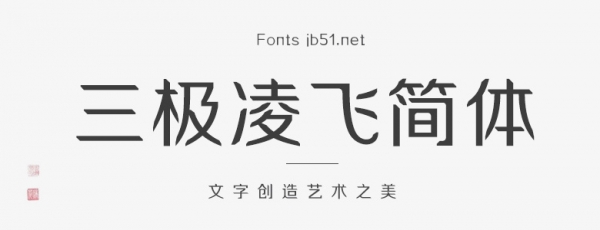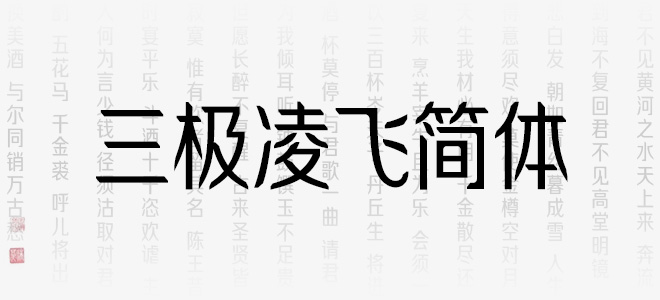
三極凌飛簡(jiǎn)體創(chuàng)意來(lái)自于鉛筆尖頭的外形,字形清新,結(jié)構(gòu)嚴(yán)謹(jǐn),起筆收筆都為斜角截?cái)啵卣髅黠@,整齊中賦予變化,易讀性強(qiáng)。適用于雜志、書(shū)刊、品牌廣告、文化用品包裝設(shè)計(jì)。
三極凌飛簡(jiǎn)體